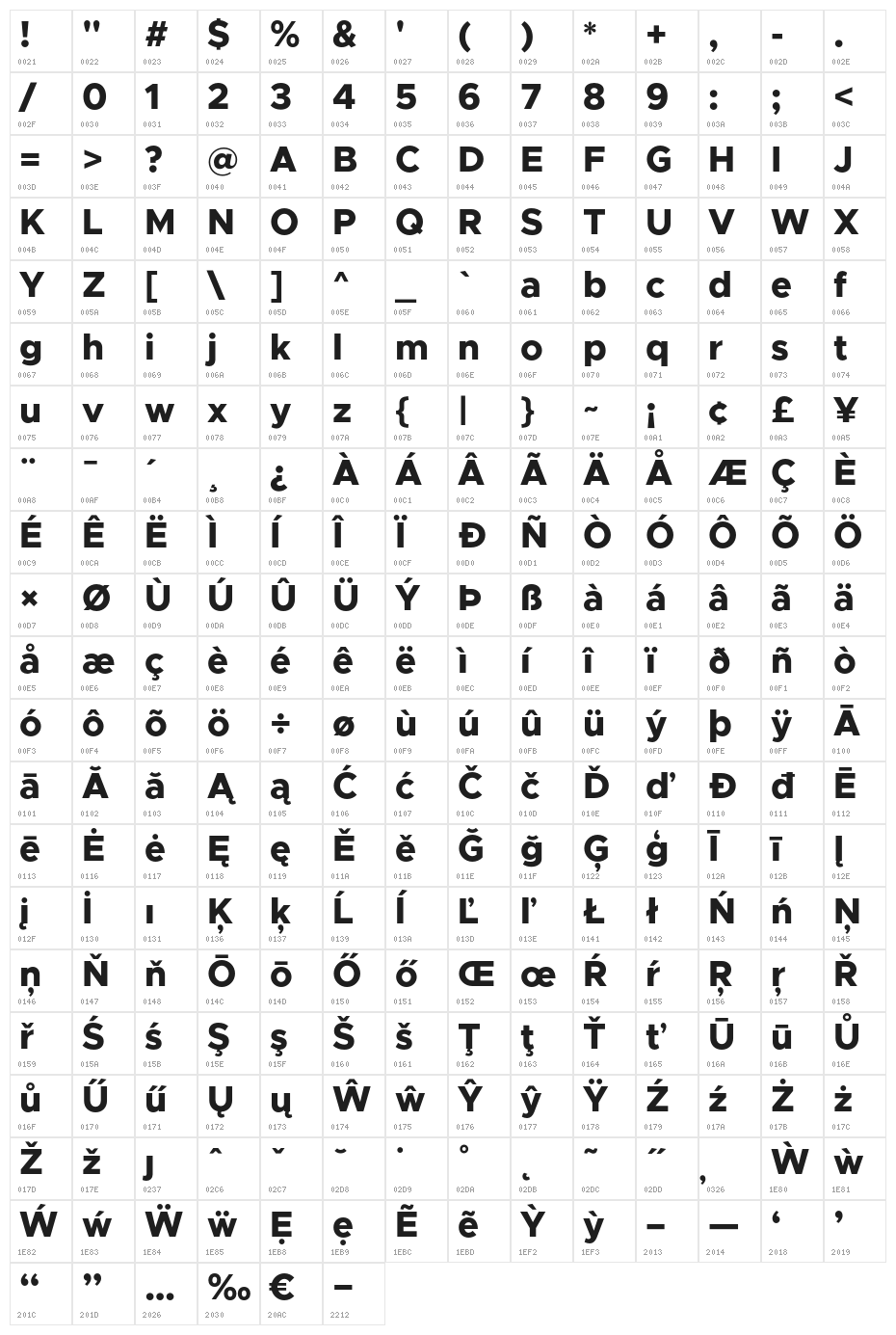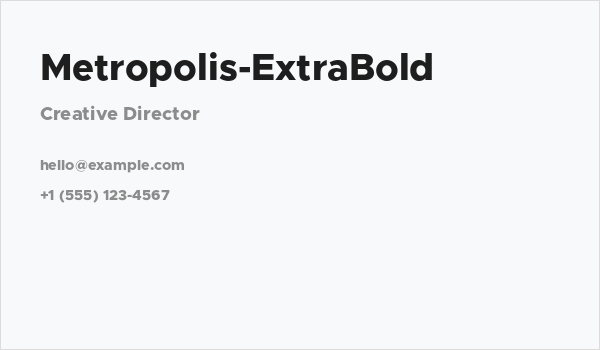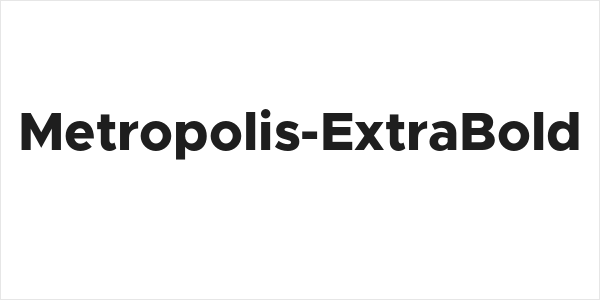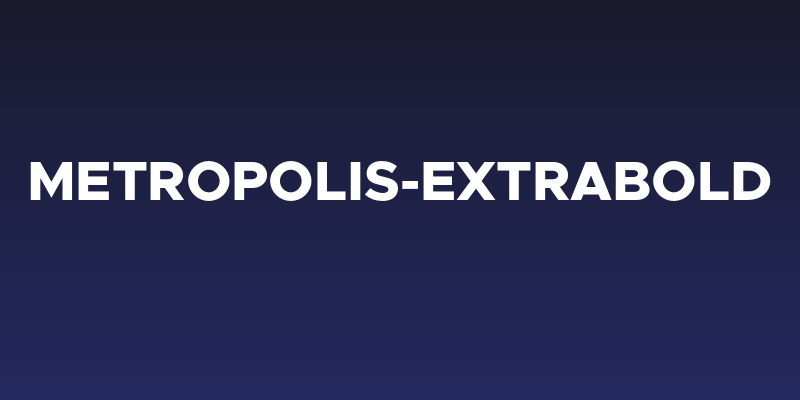
Metropolis-ExtraBold Font
Acest font include 300 caractere. Clic pe orice caracter pentru detalii.
METROPOLIS-EXTRABOLD Litere mari
METROPOLIS-EXTRABOLD Litere mici
METROPOLIS-EXTRABOLD Alte caractere
| Proiecte propuse | Ideal for branding, headlines, posters, and digital media where a strong, modern aesthetic is desired. |